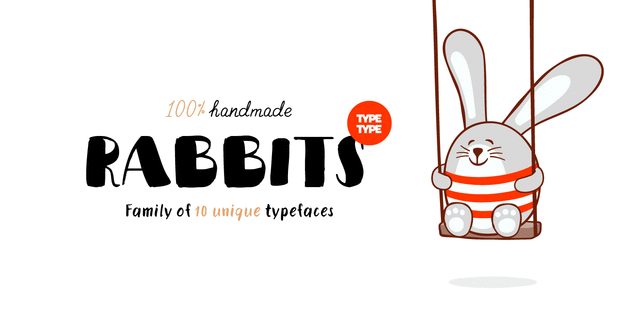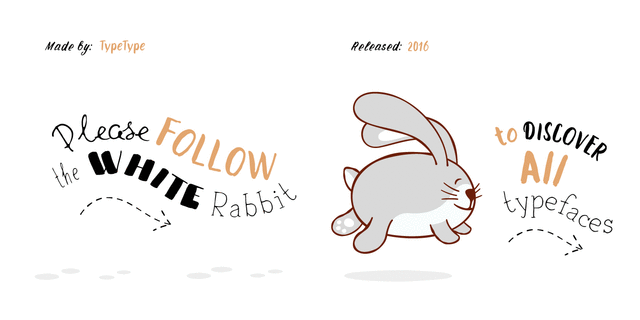
TT Rabbits – сверхэмоциональное рукописное шрифтовое семейство, состоящее из 10 разных шрифтов. Мы объединили эти шрифты по одной общей теме – детство. Используйте эти шрифты для создания любой продукции для детей – детские книжки, приложения для детей, интерьеры детских комнат.
Мы дали каждому кролику уникальное имя. Имена выстроены по буквам латинского алфавита: A — April, B — Bro, C — Chilli, D — Dummy, E — Elf, F — Fatso, G— Goody, H — Hyper, I — Idol, J — Junior. Каждый кролик имеет свой характер, поэтому вы определенно полюбите TT Rabbits. Мы использовали индивидуальный пишущий инструмент для каждого шрифта. Все шрифты изначально создавались на бумаге, а затем оцифрованы.
А какой ваш любимый кролик? Шрифт разработан Иваном Гладких в студии TypeType Fonts в 2016 году.
Асоціації з сімейством шрифтів TT Rabbits CОсобистість і характер гарнітури:
лихий, дикий, динамічний, рухливий, неохайний, нервовий, ремісничий, спекотний, спекотливий, південний, наївний, грубий, потішний, прикольний, рукотворний, дотепний, веселий, грайливий, оригінальний, карикатурний, мультяшний, живий, характерний, нерівний, гулящий, дозвільний, смачний, зелений, натуральний, природний, теплий, ламповий, апетитний, свіжий, соковитий, стиглий, домашній, пустотливий, кустарний, саморобний, артистичний, органічний, милий, симпатичний, тропічний, вернакулярний, вільний, запальний